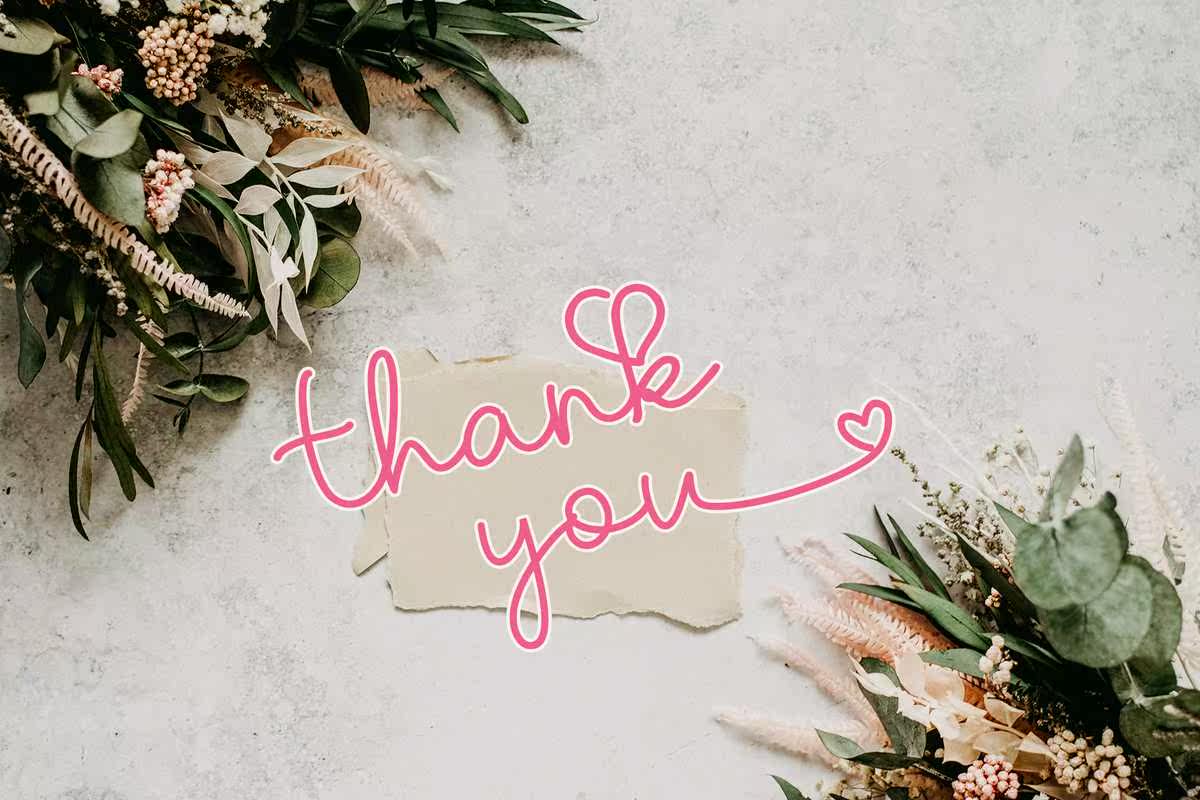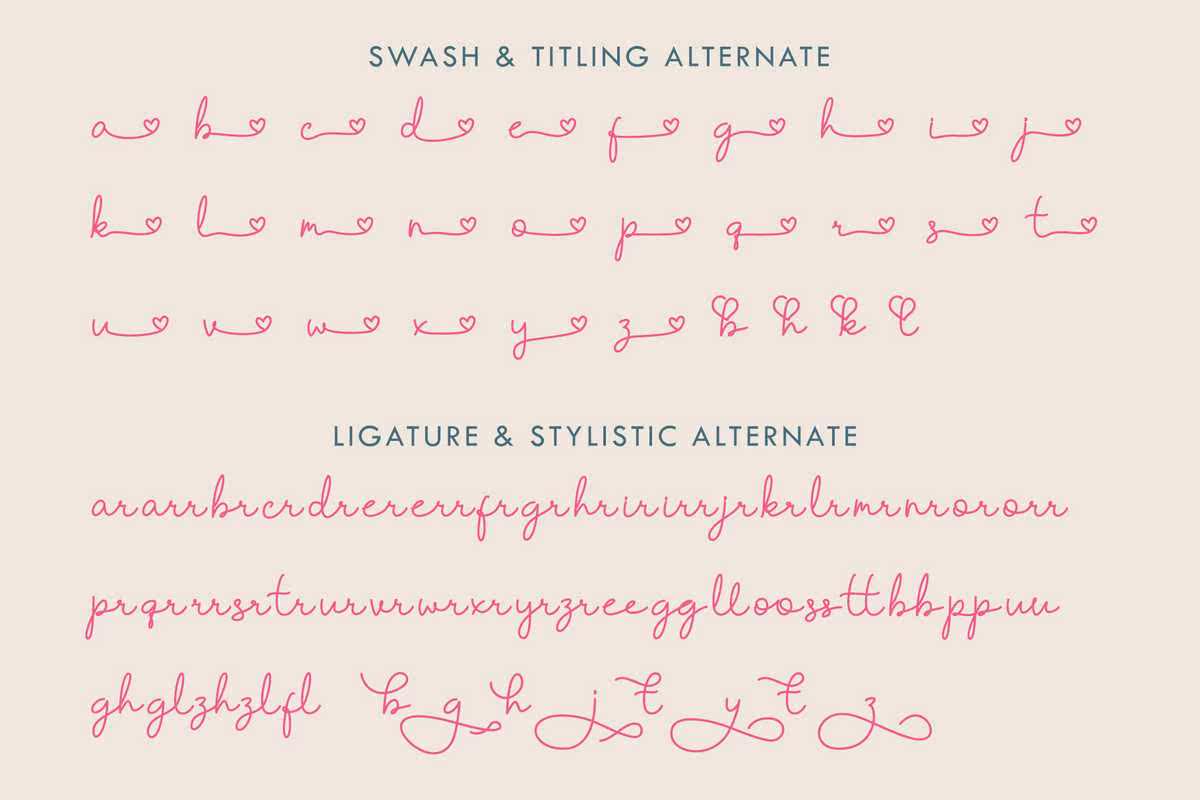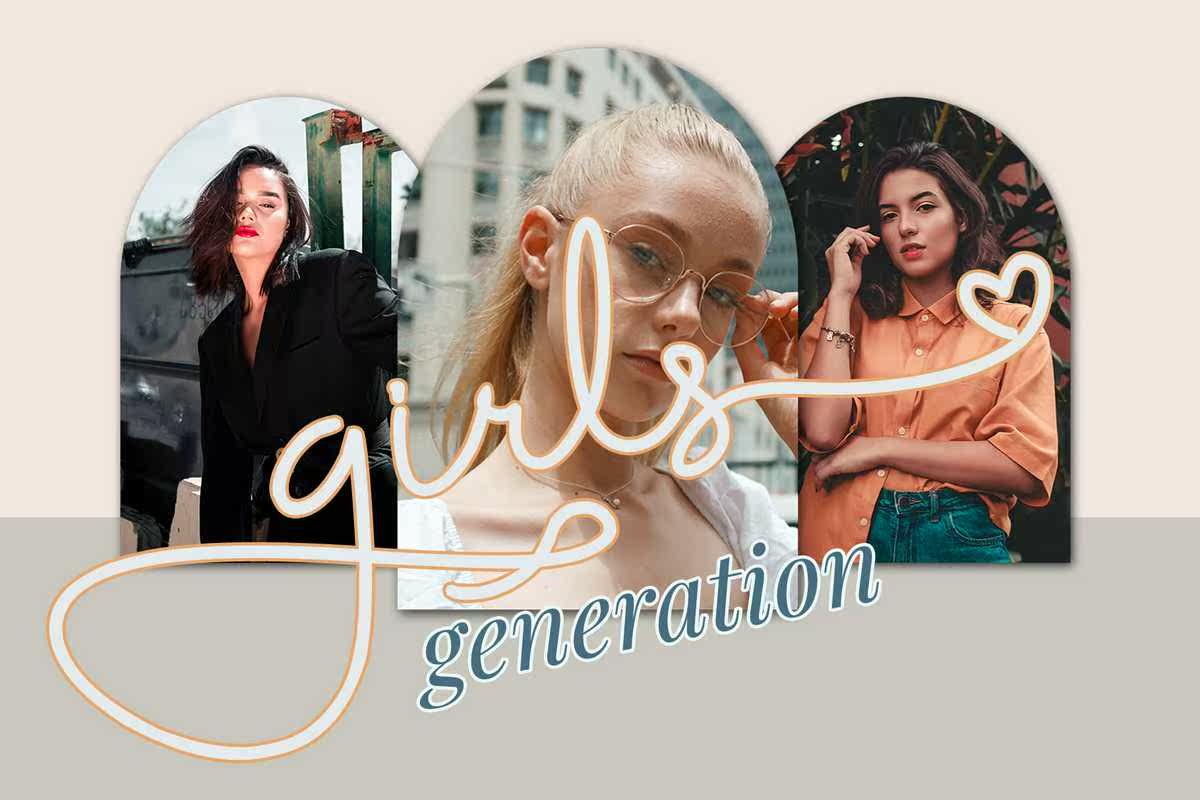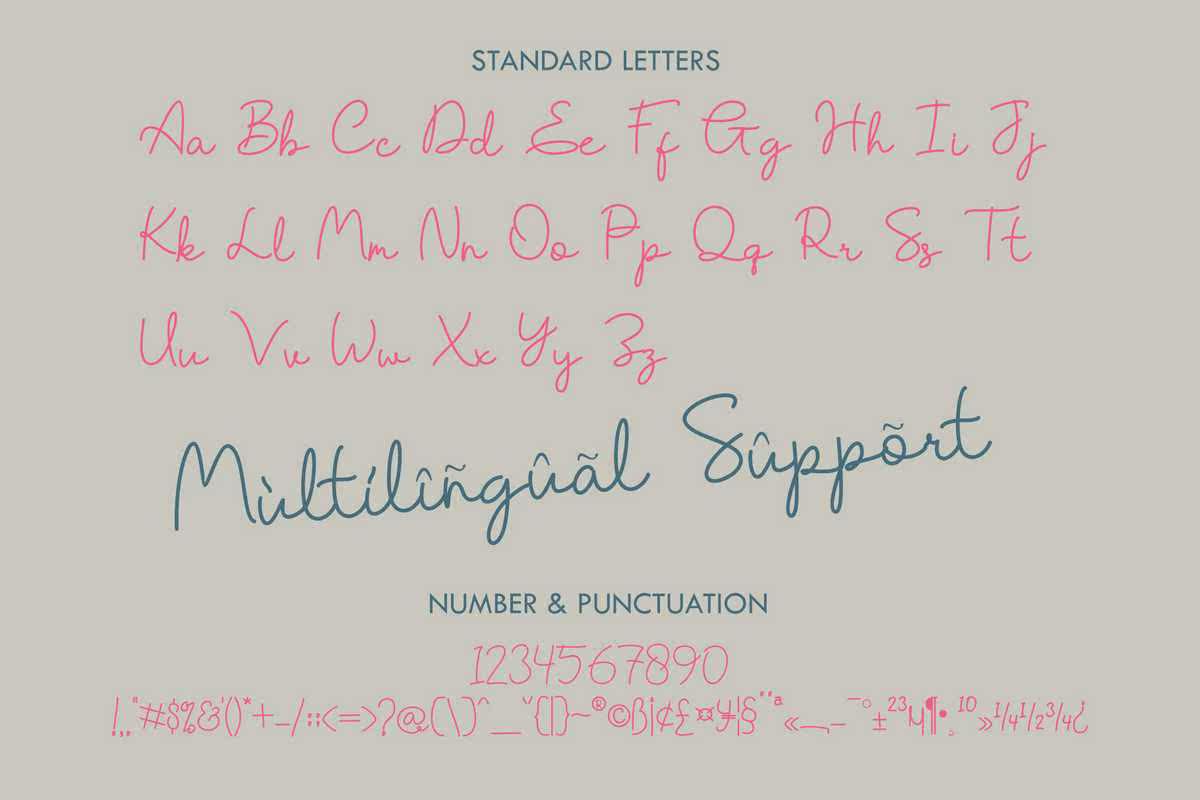
MarietteMallaby是HizartDesignStudio的独角戏。它是一个很好的周末设计,可以让你的设计具有优雅的个性。MarietteMallaby在徽标、问候卡、包装设计、耐磨性、工艺设计、任何项目、书名、婚礼宣传、包装、,还有更多。MarietteMallaby是HizartDesignStudio的独角戏。它是一个完美的设计,可以让你的设计具有优雅的个性。MarietteMallaby在徽标、问候卡、包装设计、耐磨性、工艺设计、任何项目、书名、婚礼宣传、包装等方面都是完美的。